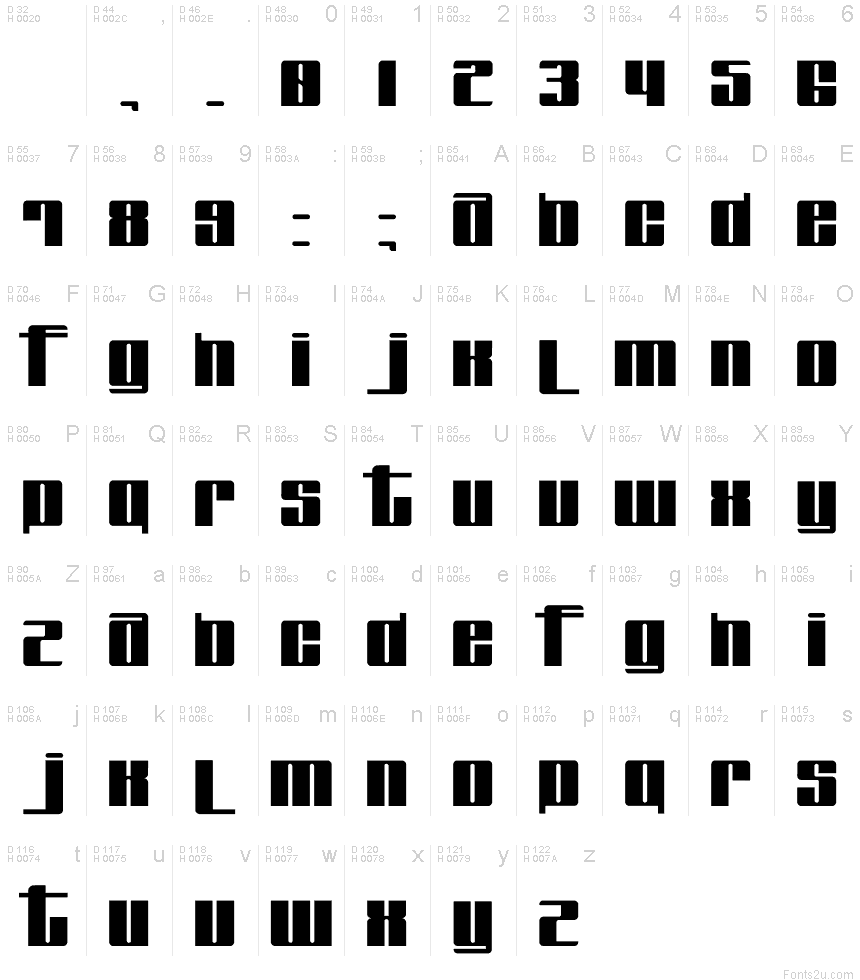
Fabulous autorstwa Steve'a Palmera to darmowy, nowoczesny font typu display o odważnym, monolitycznym charakterze. Każda litera przypomina solidny czarny filar, złagodzony zaokrąglonymi narożnikami i przecięty wąskimi pionowymi wycięciami, dzięki którym słowa „oddychają”. Przedłużona pozioma kreska wychodząca z litery F łączy znaki niczym elegancka linia w nagłówku, nadając tekstowi mocne, filmowe wejście na stronie lub ekranie.
Fabulous nadaje projektom blokowy, futurystyczny rytm, który przykuwa wzrok na plakatach, ulotkach, okładkach albumów, w identyfikacji wizualnej marek technologicznych, grafikach do gier czy wyrazistych logotypach. Wąskie światła i wysokie, pionowe formy tworzą niemal architektoniczną fakturę, czytelną nawet z dużej odległości. Ten darmowy font świetnie komponuje się z prostym bezszeryfowym krojem geometrycznym w mniejszych rozmiarach – użyj Fabulous do dużych, wyrazistych nagłówków, a tekst pomocniczy pozostaw lekki i subtelny.